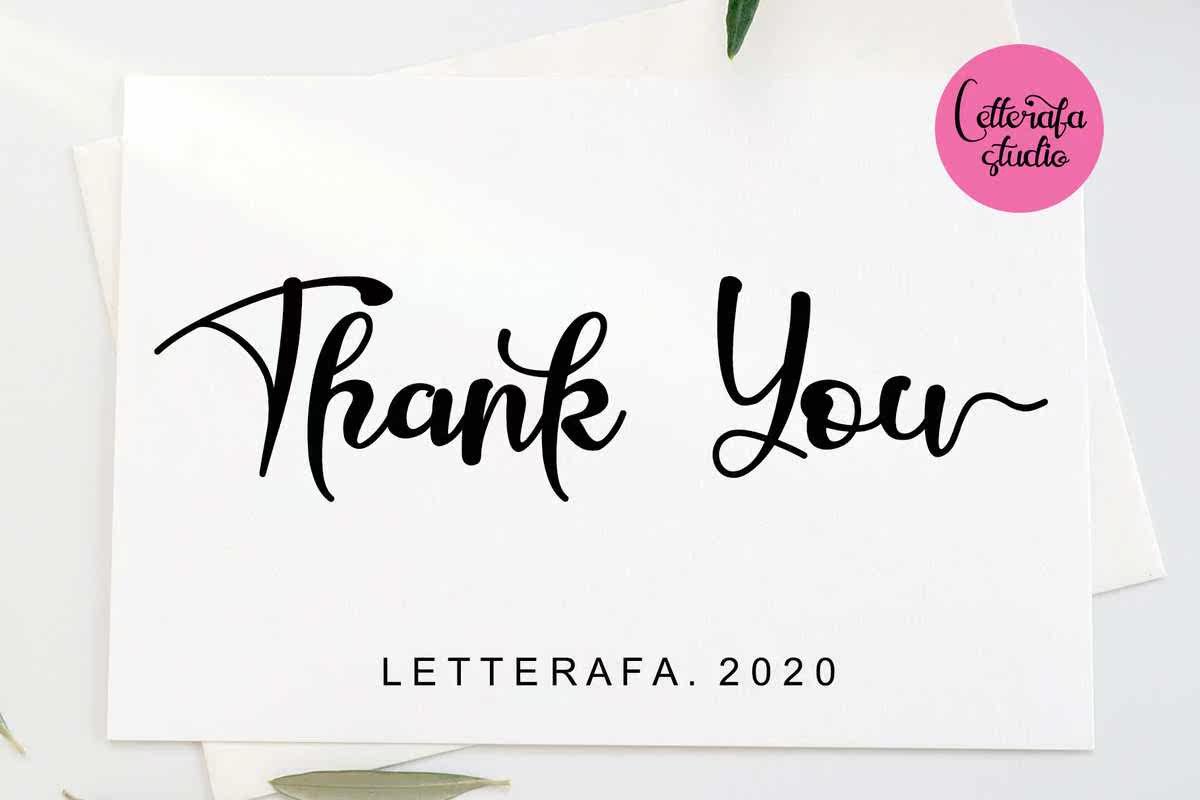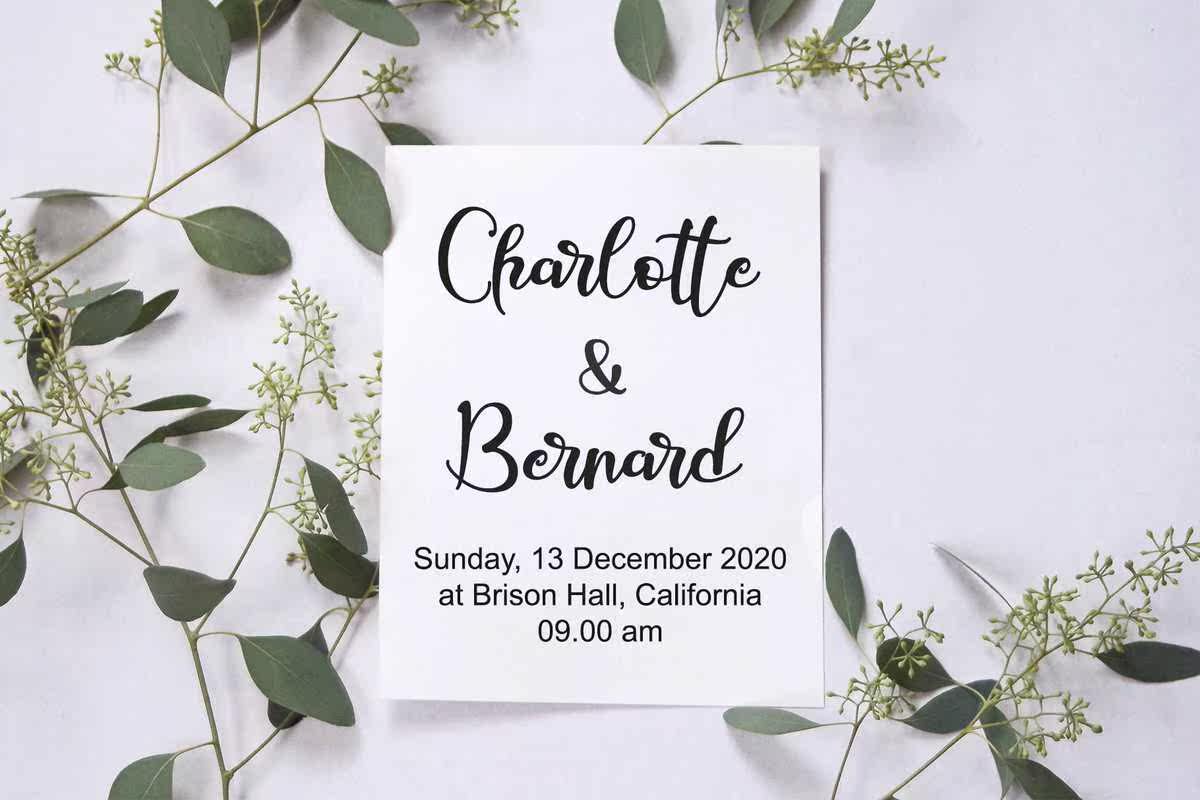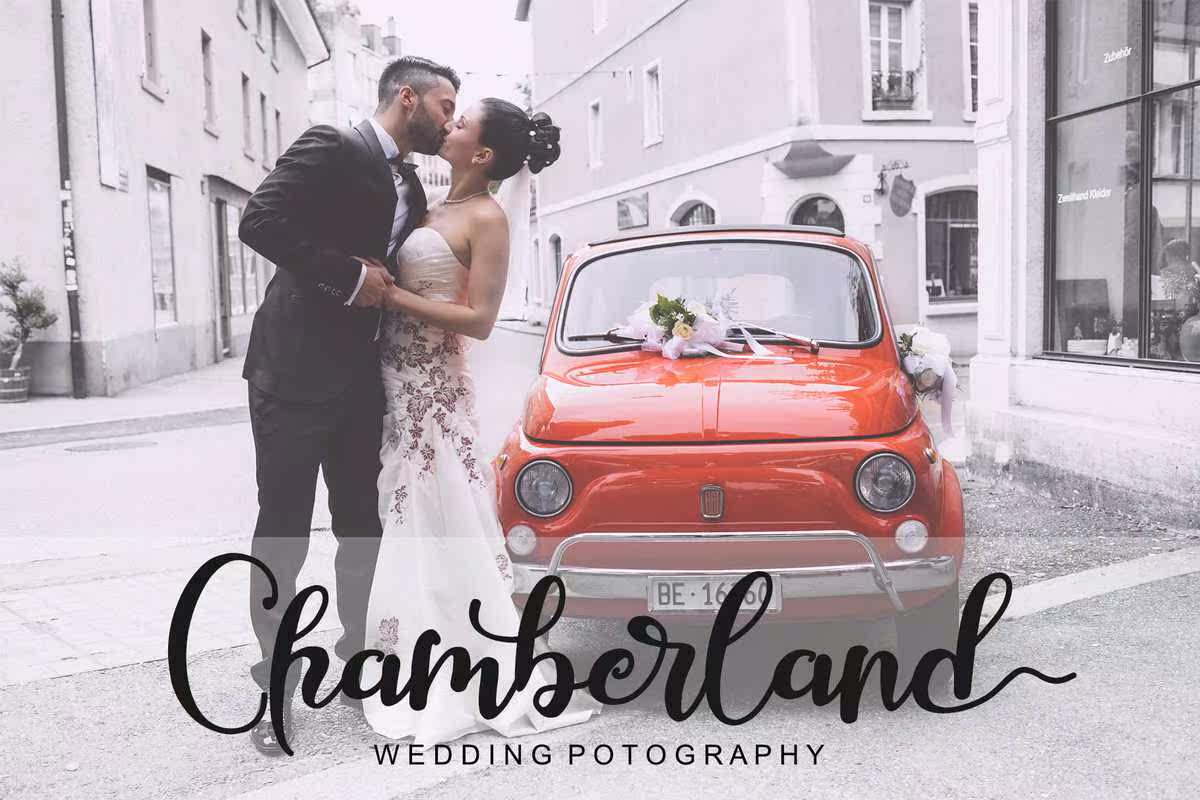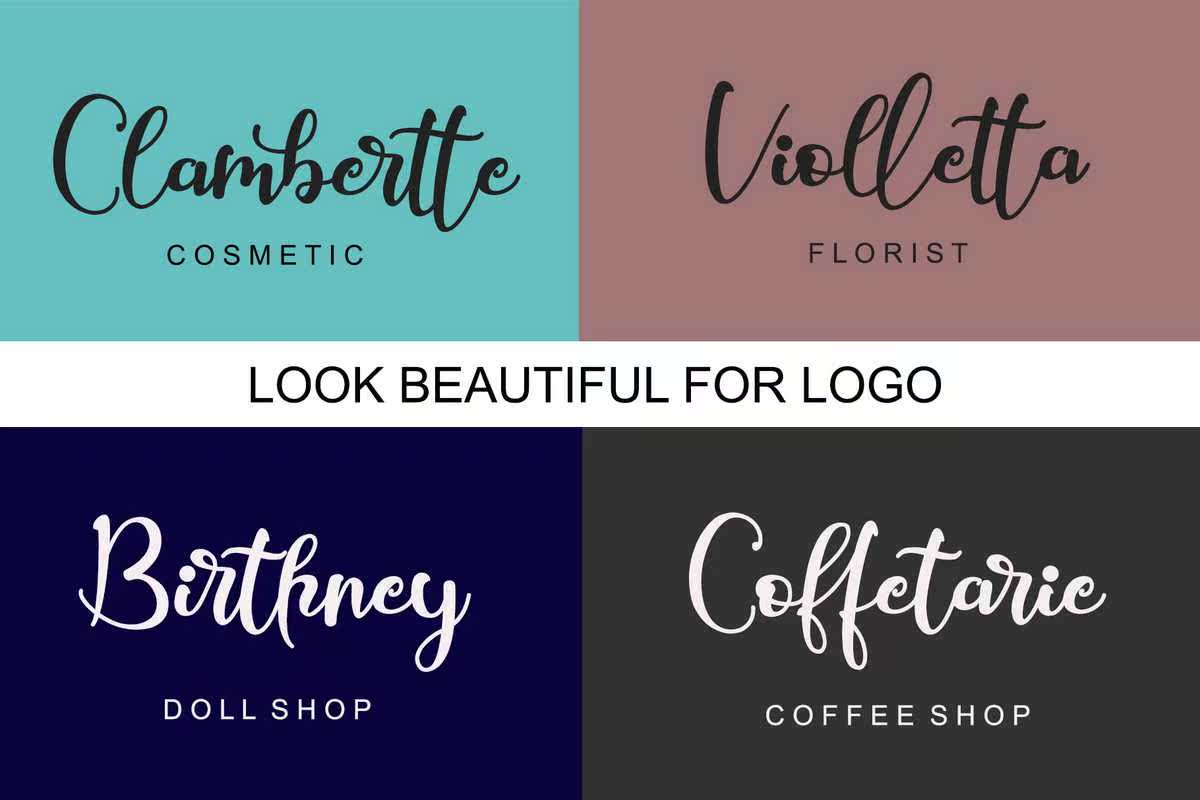
Jaggielkafont是由Yahmadafandi(LetterafaStudio)创建的。它是一个流动的字母,将使您的设计更清晰、更周全。Jaggielkafont是完美的;欢迎卡、包装设计、耐磨性、工艺设计、任何项目、书名、婚礼宣传、包装等。Jaggielkafont是由Yahmadafandi(LetterafaStudio)创建的。它是流动的字母,将使您的设计更具吸引力和周刊。Jaggielkafont是完美的;贺卡、包装设计、耐磨性、工艺设计、任何项目、书名、婚礼宣传、包装等等。